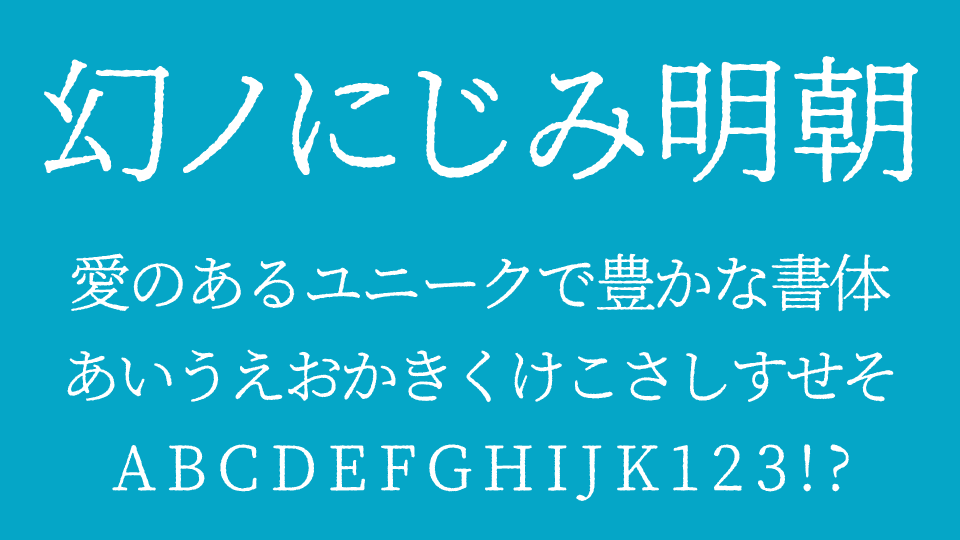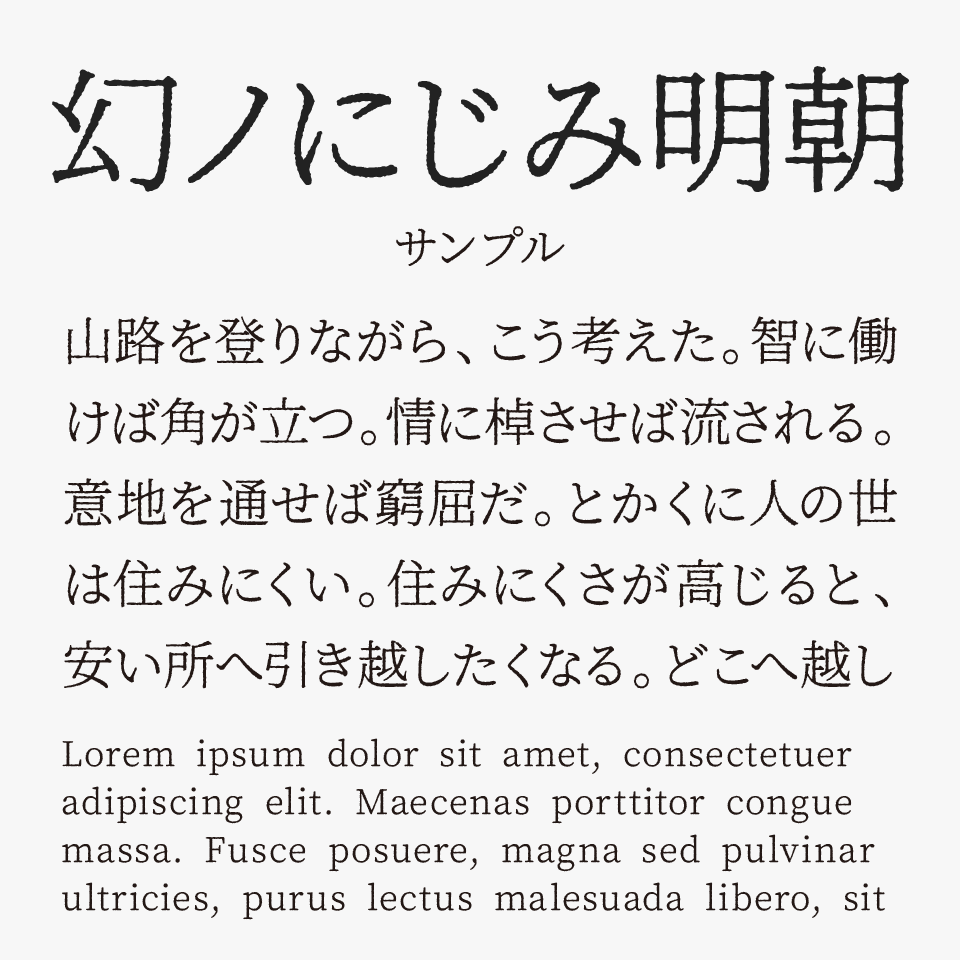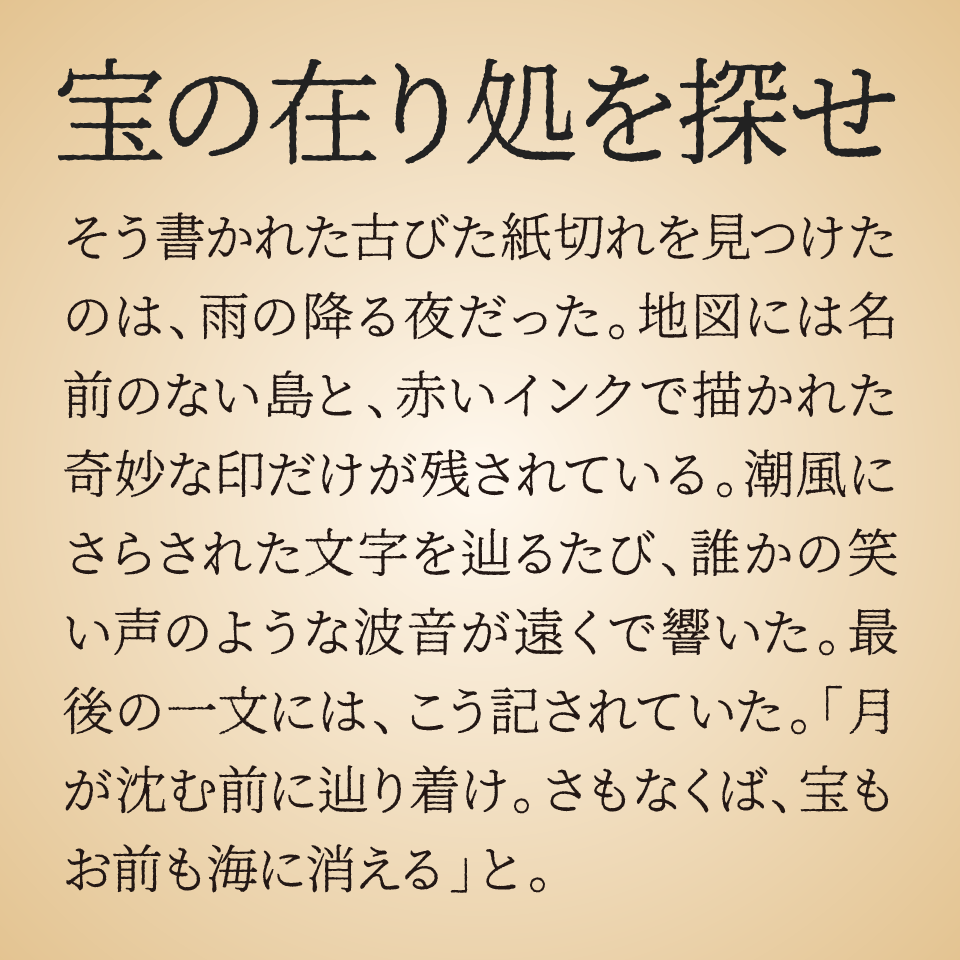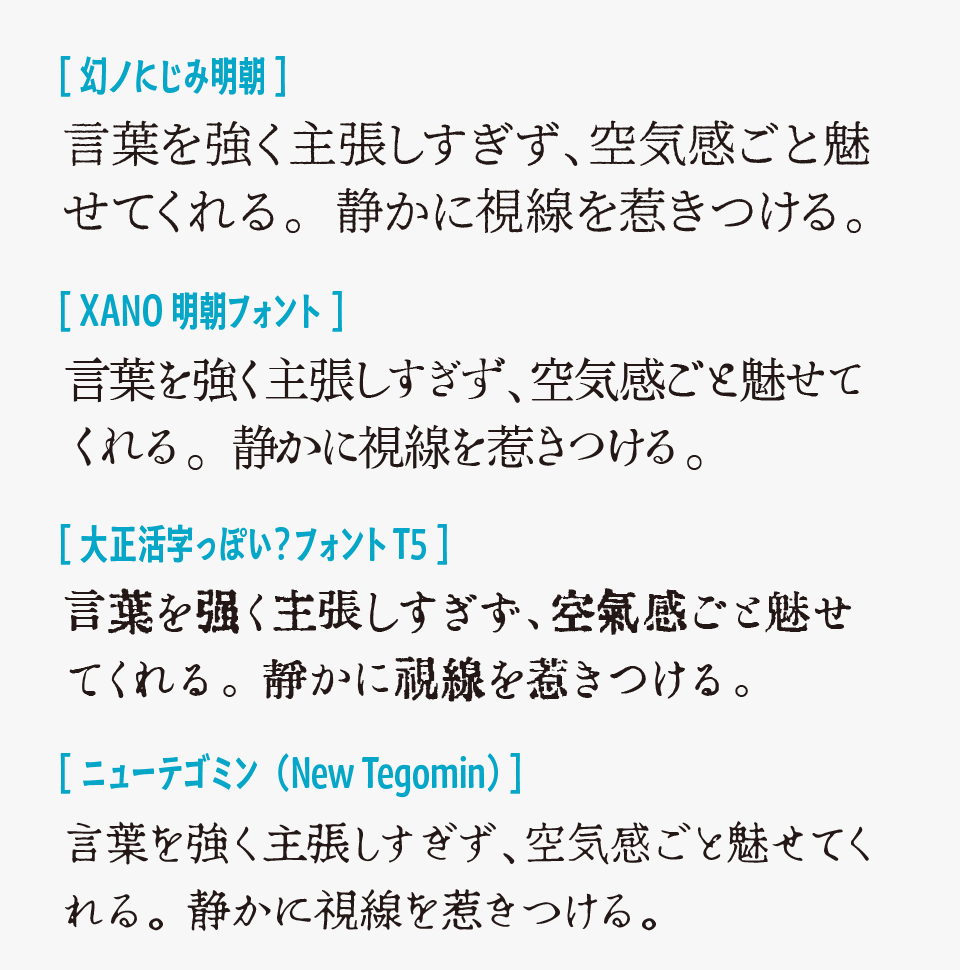
幻ノにじみ明朝(まぼろしのにじみ)
幻ノにじみ明朝(まぼろしのにじみ)フォントは、かすれた筆跡のような質感をまとった、文字のアウトラインに少しジャギジャギした輪郭が、インクの滲み風加工が施されている少し変わった明朝体フォントです。
どこか儚く曖昧な表情を加えることで、物語の余韻のような情緒を感じさせるフォントです。
インクが滲んだような文字全体の質感によって、どこかレトロでエモーショナルな空気感が漂っているフォントです。
かすれや滲みの加工が施されているため、特別なエフェクトを加えなくても、文字を打つだけで簡単に“それっぽい”雰囲気を演出できるところも魅力です。
レトロやヴィンテージ、懐かしさや感情的な空気感を出したいデザインとも相性が良く、MV風ビジュアルやサブカル系デザイン、レトロなタイトル表現などにもぴったりな便利なフォントとなっています。
幻ノにじみ明朝と、同じように滲み表現を取り入れたフォントを比較してみると、幻ノにじみ明朝は特に“繊細で感情的な滲み方”が印象的です。どこか儚さや文学的な空気感を感じられるところが魅力的なフォントです。
比較フォントは、「XANO明朝」「大正活字っぽいフォント」「ニューテゴミン(New Tegomin)」と比較していますが、どのフォントも独特な雰囲気がステキなので、あわせてチェックしてみてください。
収録文字は、ベースフォントはオープンソース「源ノ角明朝」を使用しているので、数字、アルファベット、記号、かな文字(ひらがな・かたかな)、教育漢字、常用漢字、第一水準漢字、第二水準漢字などほぼすべての文字はカバーされています。